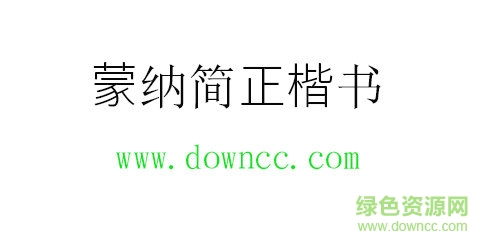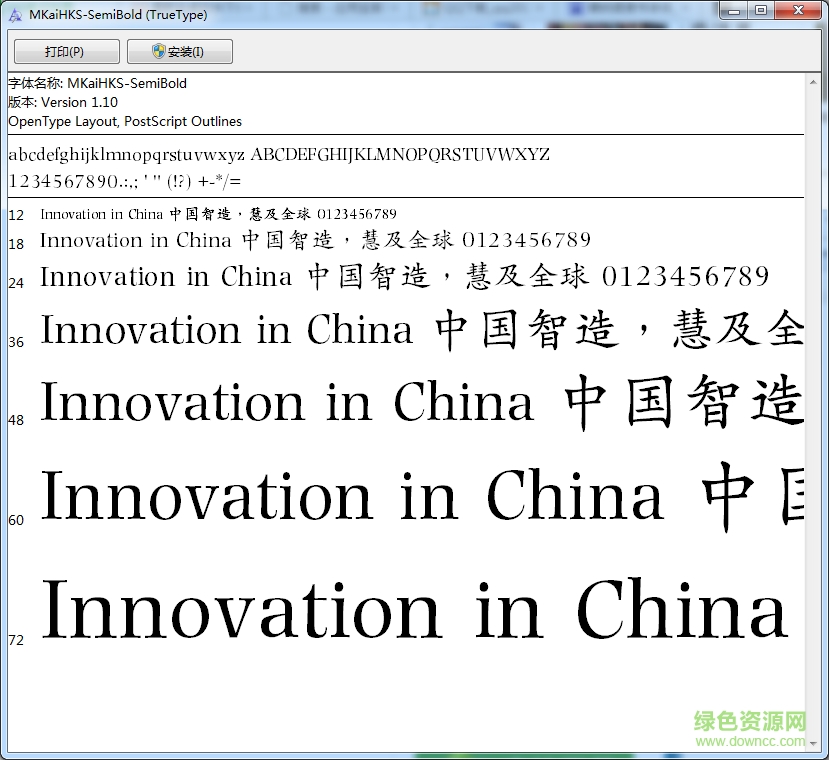
蒙納簡(jiǎn)正楷書字體是一款非常有特色的電腦字體軟件,常用于廣告設(shè)計(jì)、ppt制作、名片設(shè)計(jì)等多種領(lǐng)域,字體簡(jiǎn)單大方彰顯個(gè)性,讓你在生活中的任何方面都能使用的到哦,感興趣的朋友可別錯(cuò)過了,歡迎來綠色資源下載使用哦。
蒙納簡(jiǎn)正楷書體看起來剛勁有力,筆畫書寫起來猶如行云流水,無論是正文標(biāo)題,還是各種設(shè)計(jì)行業(yè)都可以使用哦,歡迎大家下載。